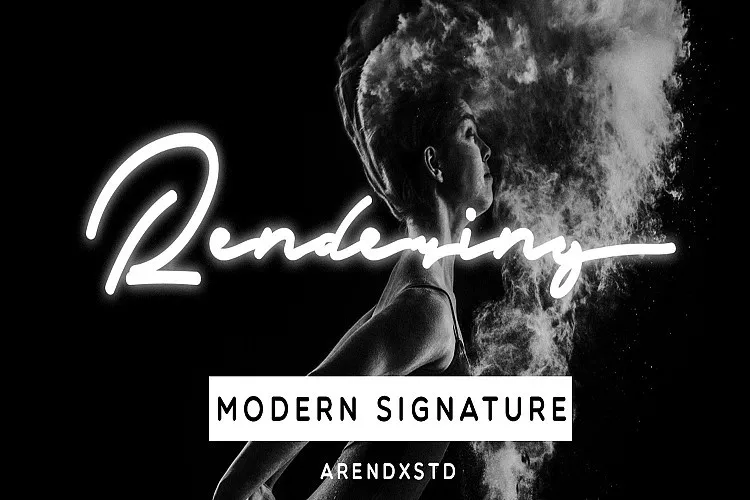
Rendering Signature Font – Download Grátis
A ‘Rendering Signature Font’ é uma opção perfeita para quem busca uma fonte moderna e elegante que combina a sofisticação do tipo manual com a praticidade de um design cuidadosamente planejado. Esta font, criada pela Arendxstudio utilizando os princípios da designer zziplex, traz consigo um estilo único e sofisticado, perfeito para diversos projetos. Ela é ideal para uso em cartas de convite, logotipos, cards de negócios, folders e até mesmo cabeçalhos de websites, proporcionando uma aparição que se destaca com sua elegância e originalidade. Com um design exclusivo e dedicado ao estilo da mão escrita, essa fonte é perfeita para atender a todas as suas necessidades gráficas. Ela não apenas oferece um visual único e moderno, mas também garante uma combinação harmoniosa entre todos os caracteres, resultando em uma experiência de leitura extremamente fluida e envolvente. Seja você designer ou criativo digital, a ‘Rendering Signature Font’ é certamente uma opção que merece ser explorada para adicionar um toque especial aos seus projetos.